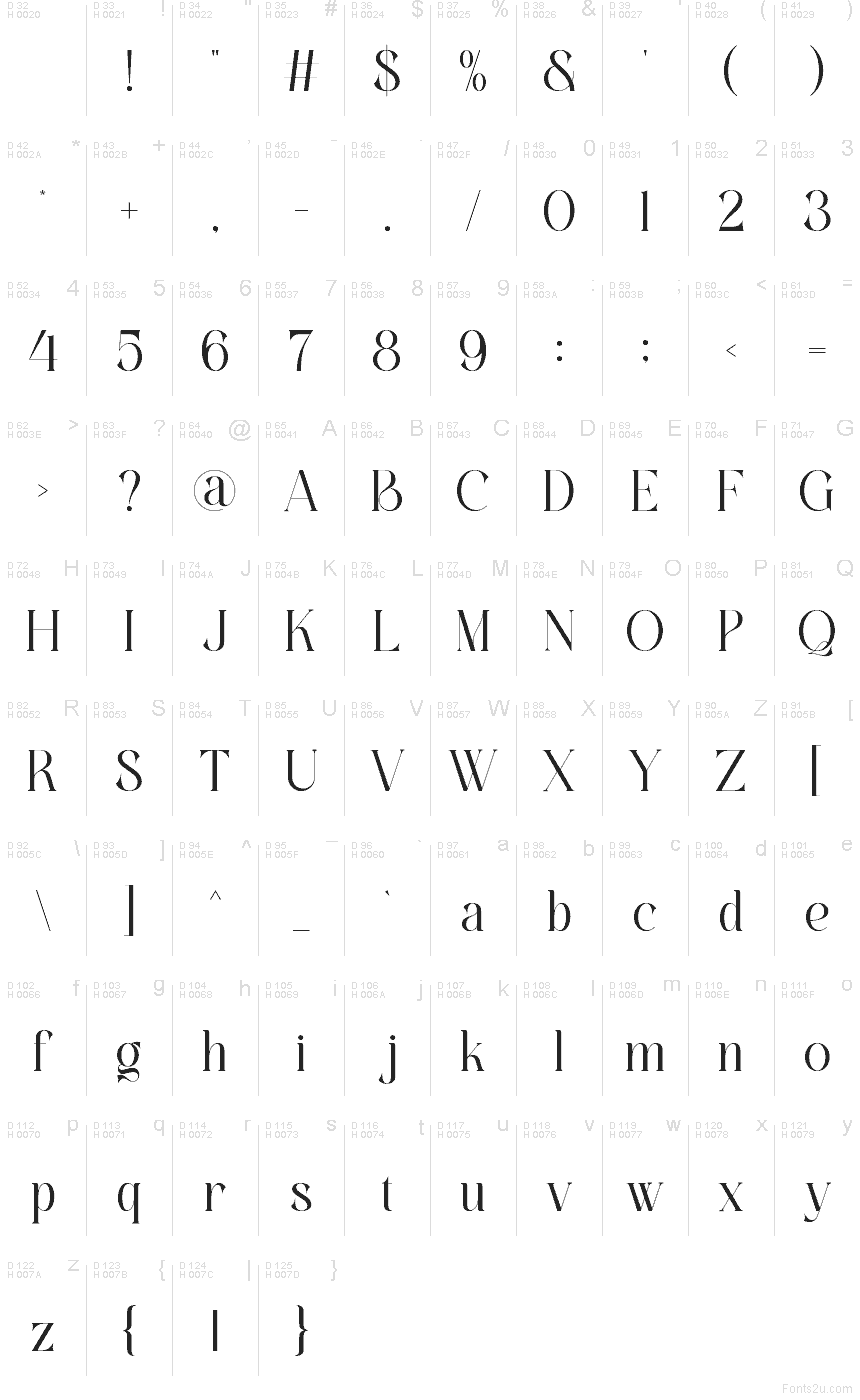
Airen, da Ermedia Studio, é uma fonte display com serifa gratuita e de alto contraste, com curvas amplas, traços finíssimos e maiúsculas largas e esculturais. As variações extremas na espessura do traço conferem à composição uma elegância refinada e inspirada na moda.
O setor editorial de moda é o seu ambiente ideal, especialmente em títulos de revistas e aberturas editoriais que se destacam por grandes escalas e detalhes meticulosos. Essas mesmas formas altas e expressivas combinam perfeitamente com embalagens de perfumes, identidades visuais de beleza e cartazes de eventos sofisticados. Sobre fotografias de retratos ou imagens de produtos, as travessas finas e as curvas generosas ecoam linhas delicadas, em vez de atuar como mero texto neutro.